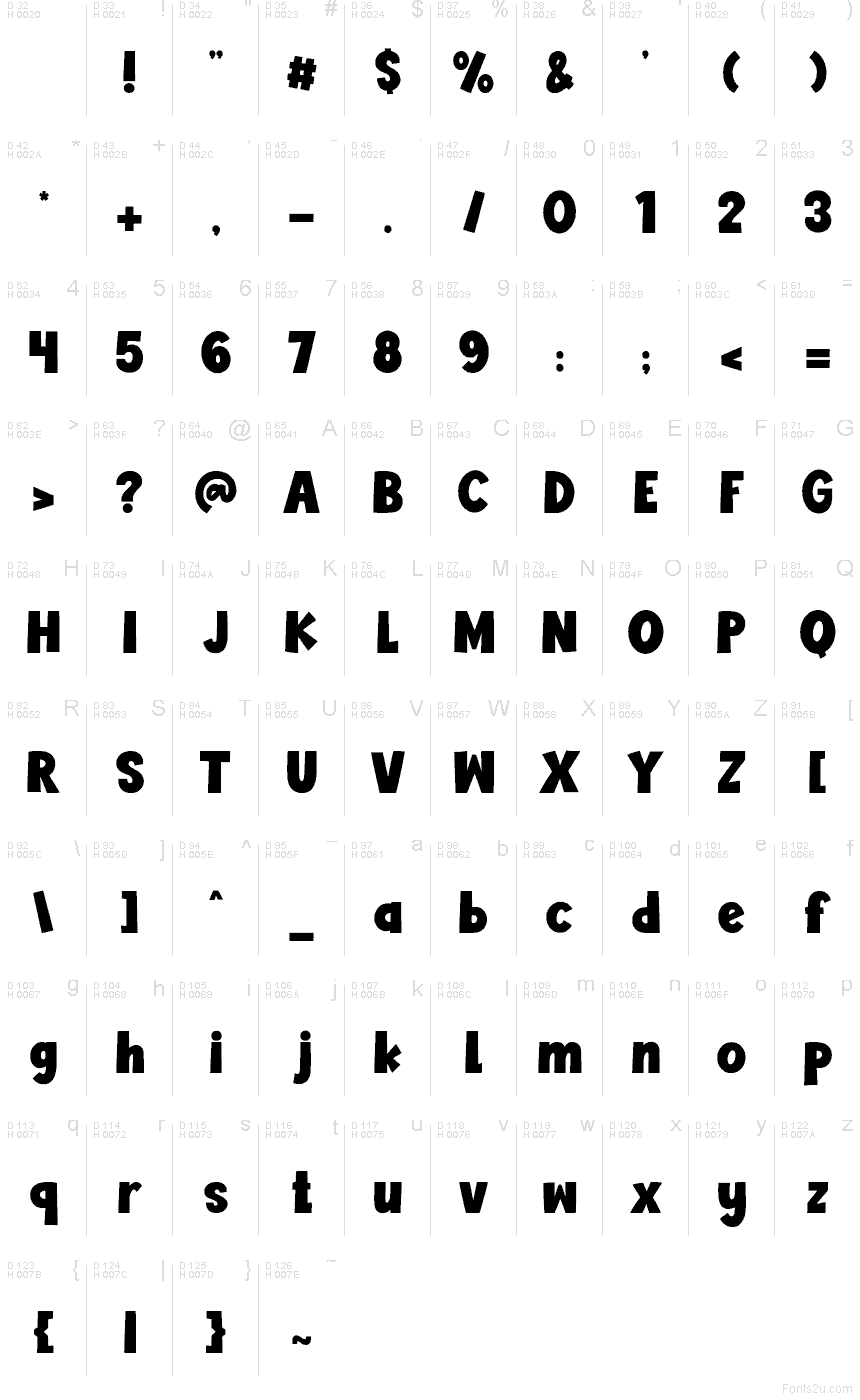
Sugar Loved od SiapGraph to darmowy, rysunkowy krój pisma o gęstej, syropowatej formie i miękkich, napuchniętych literach. Znaki wydają się być wyprofilowane i lekko opadające, z szerokimi krzywiznami, łagodnymi łączeniami i przyjaznym ciężarem, który bardziej kojarzy się ze słodyczami niż z komiksem.
Naturalnie pasuje do opakowań słodyczy, zaproszeń na przyjęcia dla dzieci, zabawnego brandingu kawiarni, logotypów w stylu naklejek oraz krótkich nagłówków na plakatach, gdzie krój o tak dużej miękkości potrafi sam nadać odpowiedni nastrój. Użyj go, gdy potrzebujesz dużych, radosnych napisów, zwłaszcza na tytułach czy okładkach, ponieważ zaokrąglone kształty sprawiają, że nawet prosty tekst nabiera wyjątkowej słodyczy.